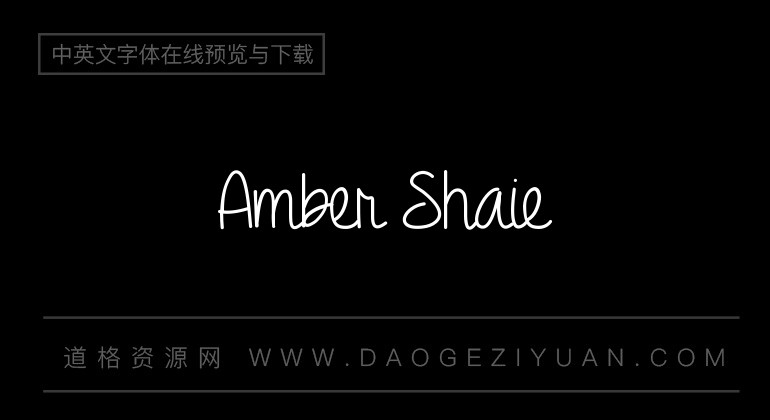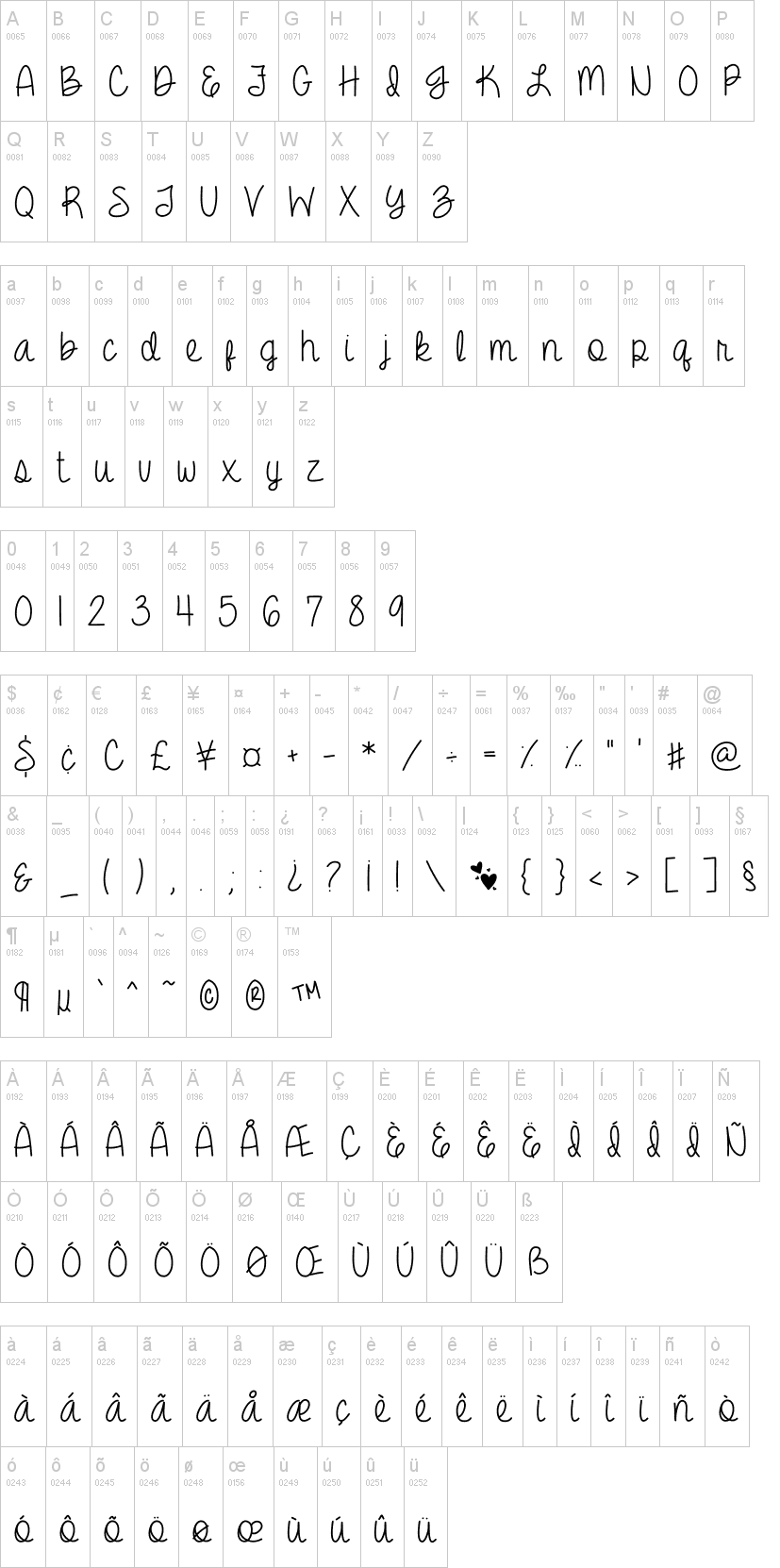
Amber Shaie
Amber Shaie 字体是一款简洁的英文字体,它的字体风格清新简约,字形圆润,比较细腻,适合用在报刊杂志、海报、书籍封面、网页设计等等,具有较高的可读性和视觉冲击力。Amber Shaie 字体支持多种语言,支持中文,英文,日文,韩文等,支持多种字体格式,如TTF,OTF,WOFF,EOT等,可以让您更加方便、快捷地进行设计。
Amber Shaie是一款非常不错的手写艺术字体,具有很好的视觉感,适合于文化类的宣传设计、商业类品牌的广告和产品包装设计以及个性化文字排版等较多场景。
Amber Shaie字符映射图